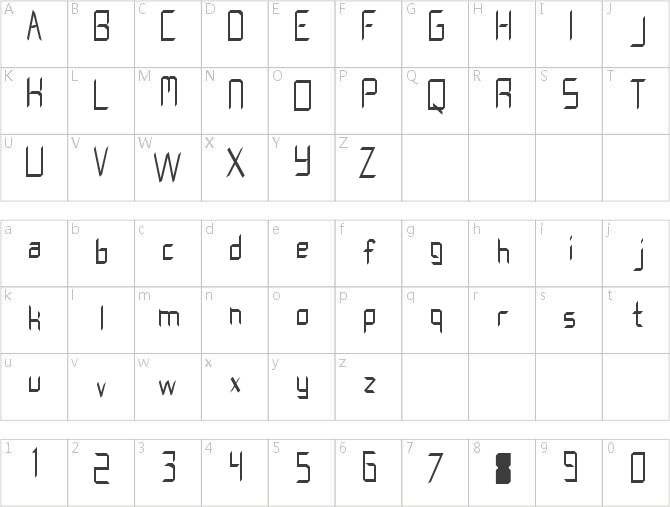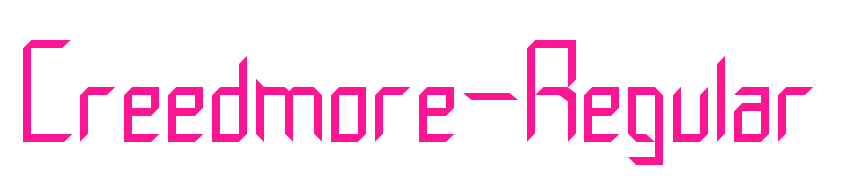
Creedmore-Regular 詳情頁(yè)
Creedmore-Regular字體字庫(kù)是一款讓人賞心悅目、百看不厭的英文字體,適合各類廣告和產(chǎn)品包裝設(shè)計(jì)應(yīng)用,字體大小0.04MB,格式為ttf字體,上傳用戶是隨緣゜,作者/版權(quán)方為未知